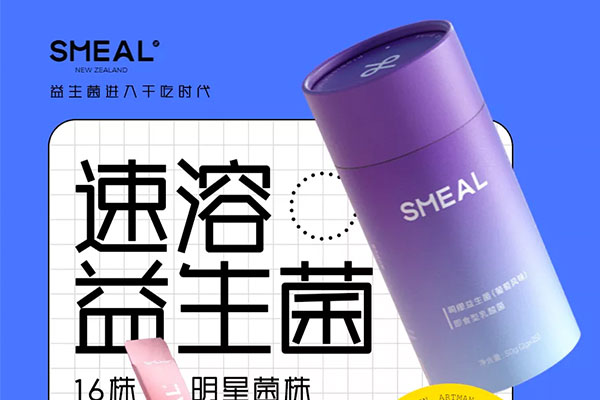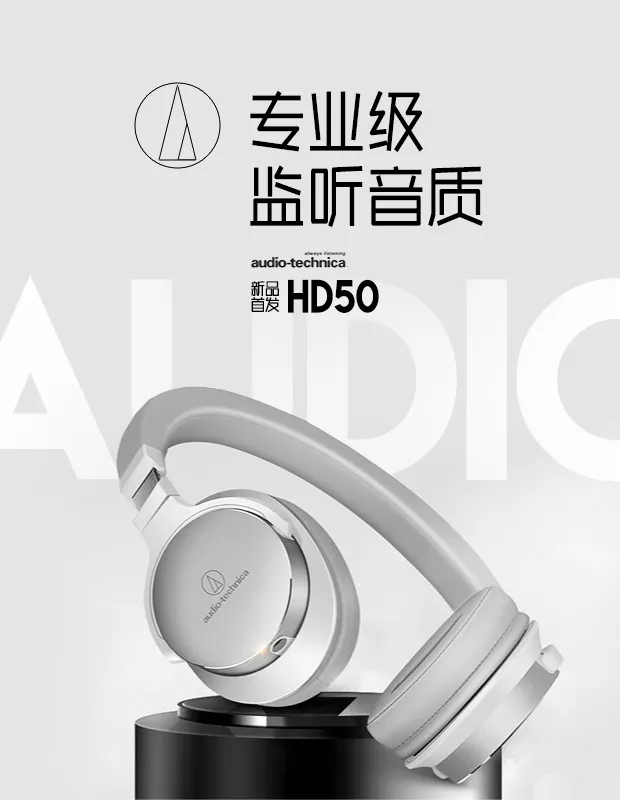
庞门正道细线体
庞门正道细线体是知名大V庞门正道委托胡晓波工作室设计推出的一款免费商用字体。
在庞门正道的第八个年头,作者即将发布第九款字体。他曾与胡晓波工作室合作开发全新字体,虽然计划免费商用,但对方作为商业机构不可能无偿制作,最终友情折扣后的制作费用超过十万。该字体在2020年完成,但因作者同时制作其他字体而延迟至2021年12月24日发布。这是作者可能发布的最后一款字体。他强调,以庞门正道名义发布的字体完全免费商用,包括企业LOGO设计。他已经投入了大量资金制作免费字体,虽然并未带来收益,但为更多品牌和设计师节省了过亿的字体授权费。他并未因此感到失望,反而因百万人使用庞门正道系列字体而感到开心。最后,他宣布全新庞门正道系列字体——庞门正道细线条登场!
庞门正道细线体效果预览
庞门正道细线体字体效果预览